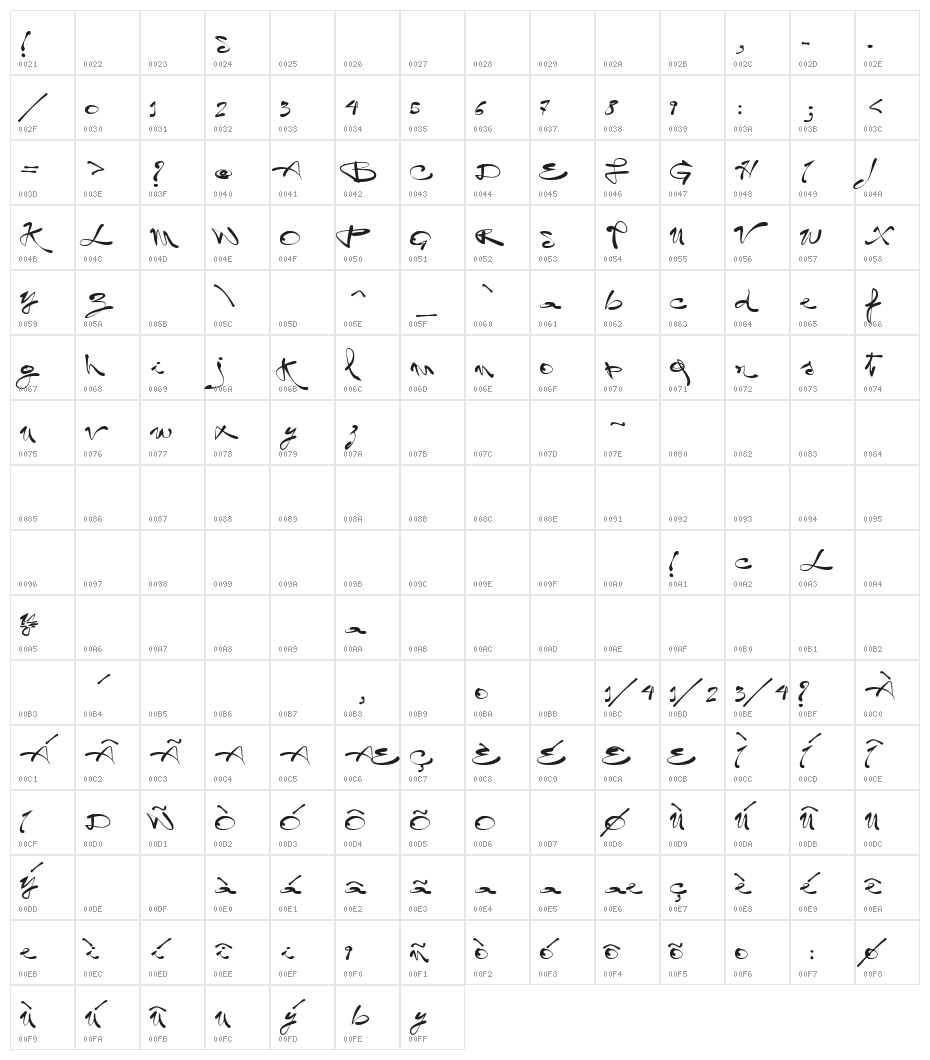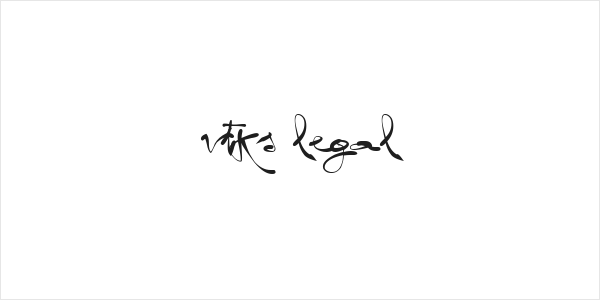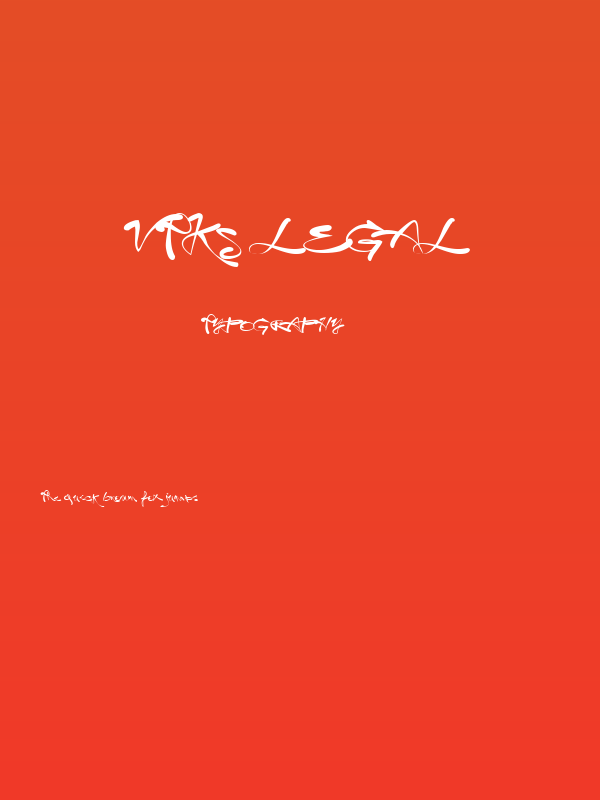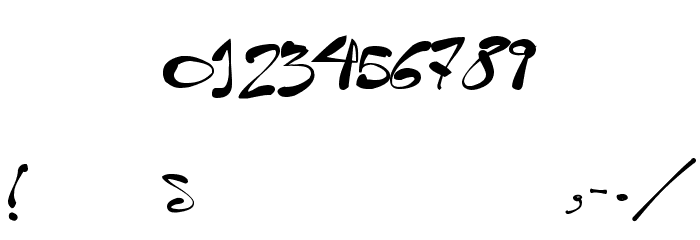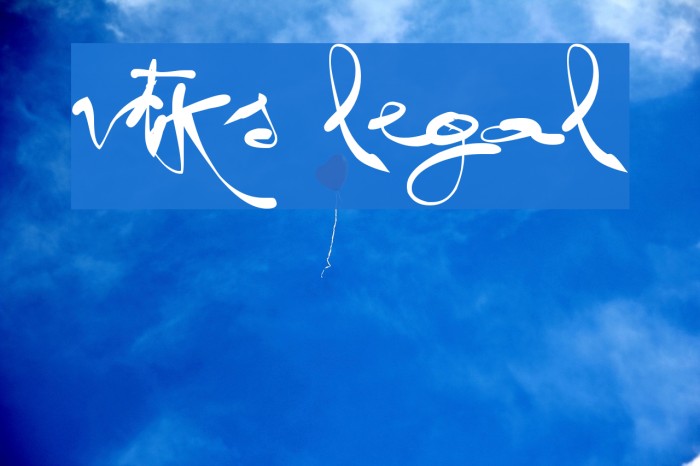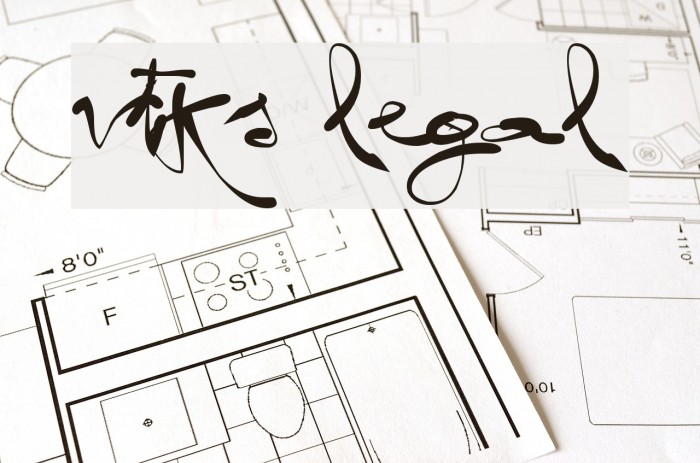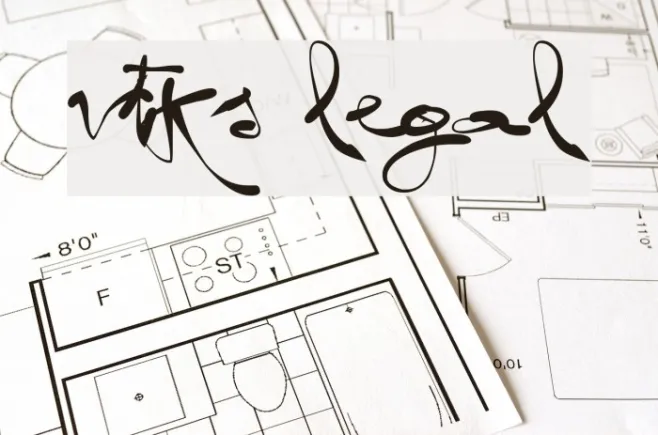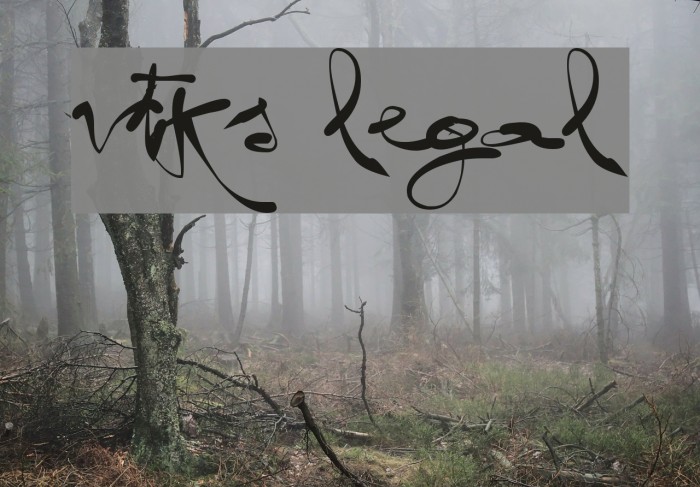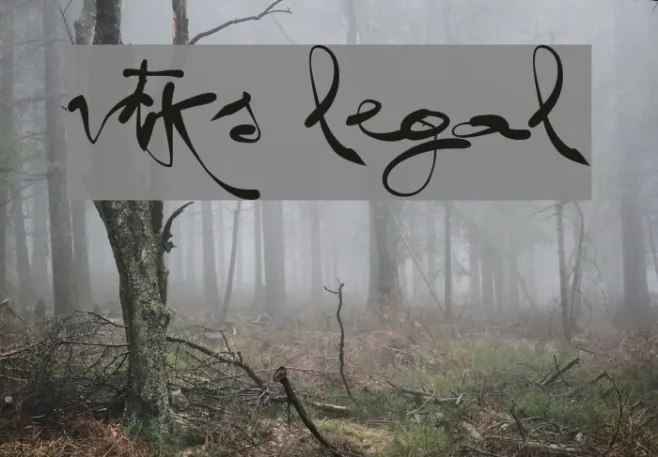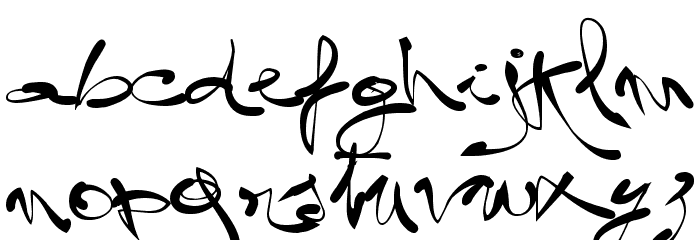
vtks legal Font
| Progetti proposti | Ideal for creative projects such as album covers, posters, and branding materials that require a distinctive and artistic touch. |
vtks legal